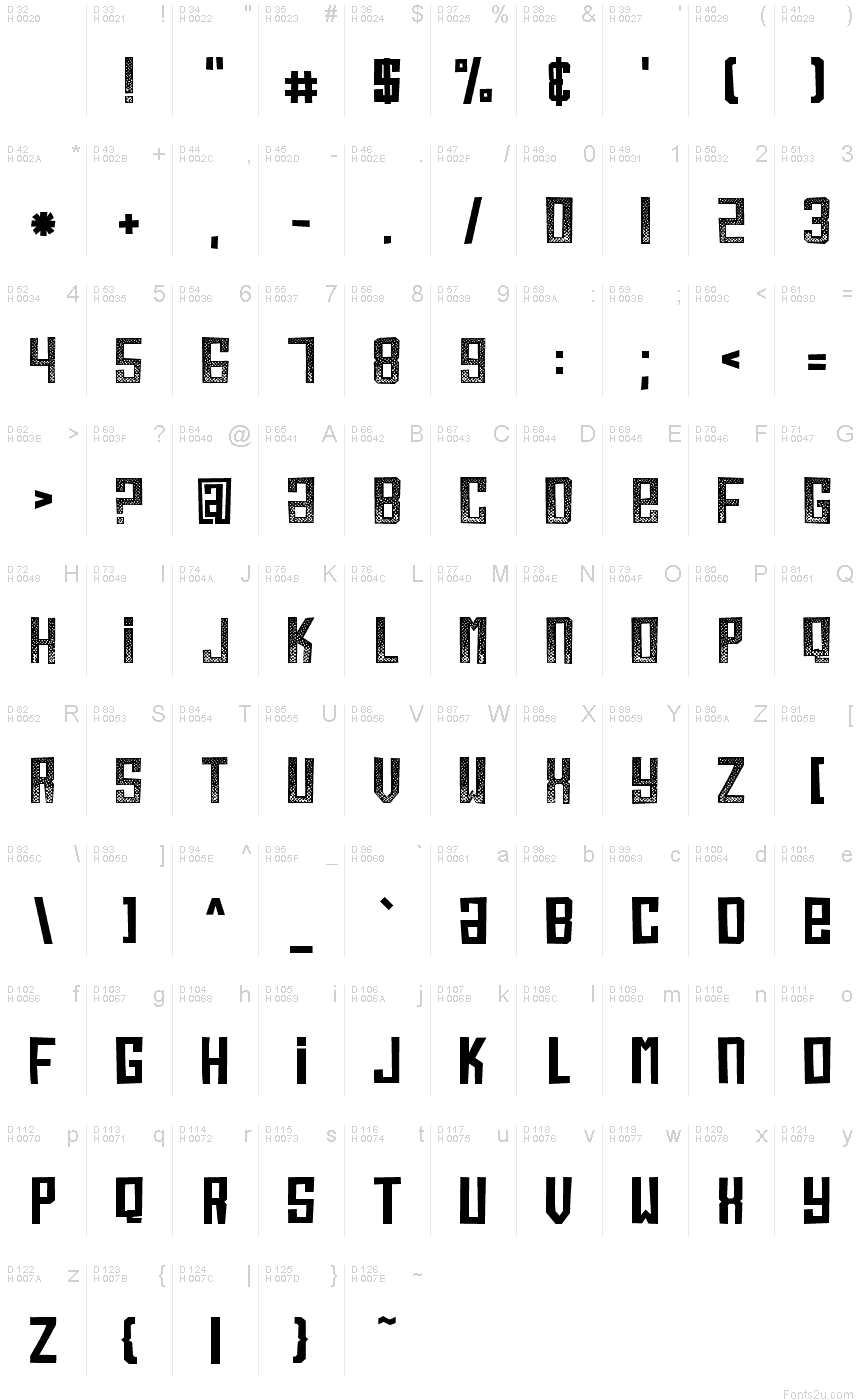
BooBooKitty od Living End je bezplatné, erodované titulkové písmo s masivními, hranatými znaky, které působí, jako by byly natištěny na kartonu. Vnitřní skvrny a otřepené okraje mu dodávají syrový vzhled jako z fotokopie – na první pohled výrazné, zblízka drsné, jako když inkoust vynechává na opotřebovaném papíře.
BooBooKitty skvěle funguje na punkových plakátech, hororových či halloweenských upoutávkách, grungeových letácích, logách pro skate nebo streetwear značky, grafice na obnošená trička, názvech indie her a obalech ve stylu samolepek. Nastavte ho ve velkém, aby vynikla jeho eroze, a poté ho zkombinujte s čistým bezpatkovým písmem na data, popisky nebo drobné texty – tento bezplatný font na sebe strhne pozornost, zatímco to druhé písmo vyřeší detaily.